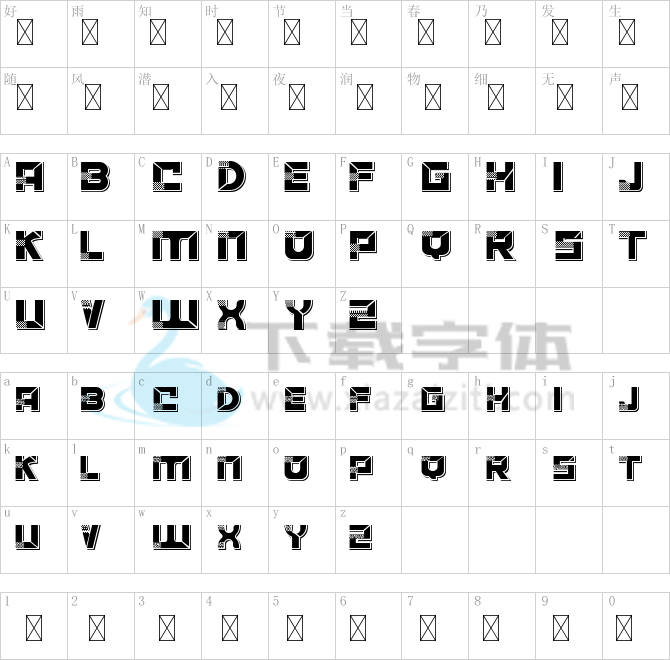
ACCELERARE Demo Shadow.ttf字体下载,这款字体结构工整、笔画清晰,兼顾美观与易读性,适用于标题、正文、海报、包装、LOGO 等多种场景。字形优雅稳定,风格百搭耐看,适配日常排版与创意设计,让文字呈现更舒适、更具质感。ACCELERARE Demo Shadow.ttf字体下载一笔一画,皆是细节,以均衡的比例、流畅的线条打造舒适视觉体验,字形端正大气,风格简约现代。无论是商业设计、品牌宣传还是日常排版,都能轻松驾驭,让文字更有格调与力量。ACCELERARE Demo Shadow.ttf字体下载字体下载。